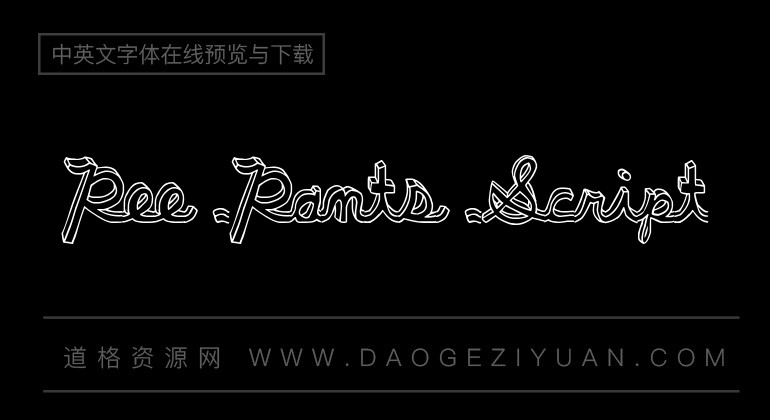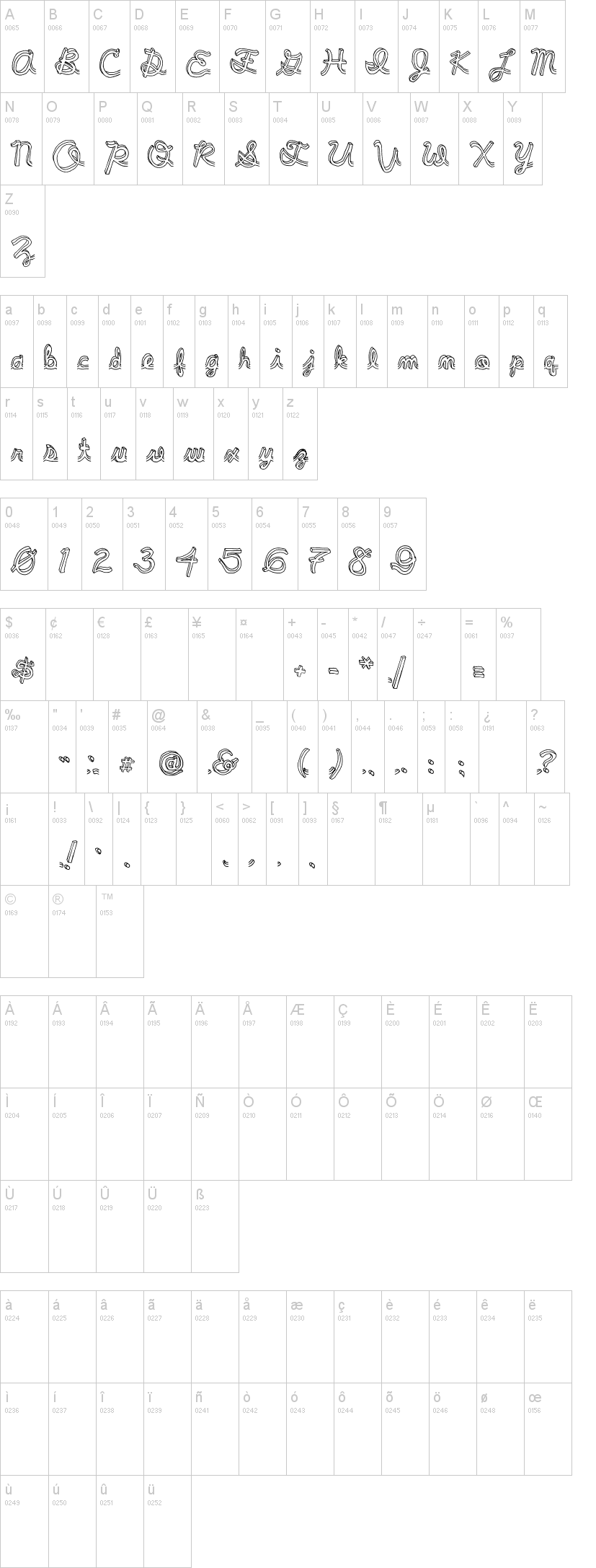
Pee Pants Script
Pee Pants Script 是一款由 Pee Pants 公司推出的脚本字体。它有着清新而又充满活力的外观,适合用于标志、广告、海报和网页设计等多种场景。它的字体曲线流畅,让字体变得更加生动,更容易引起人们的注意。此外,Pee Pants Script 字体还具有良好的可读性,使得文字更加清晰易读,从而提高文档的可读性。
Pee Pants Script是一款非常不错的手写艺术字体,具有很好的视觉感,适合于文化类的宣传设计、商业类品牌的广告和产品包装设计以及个性化文字排版等较多场景。
Pee Pants Script字符映射图